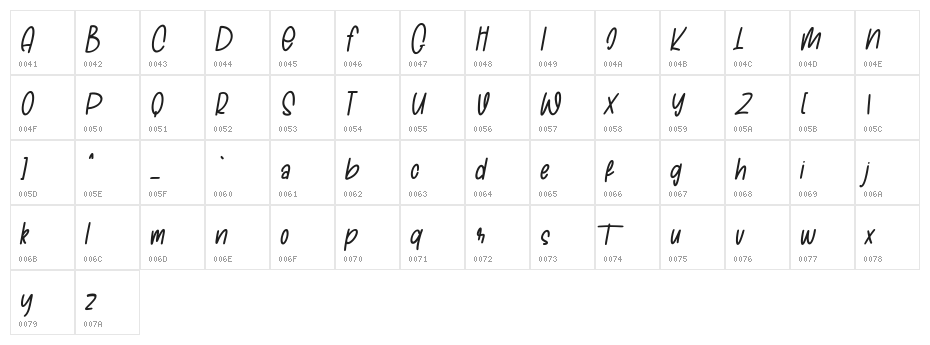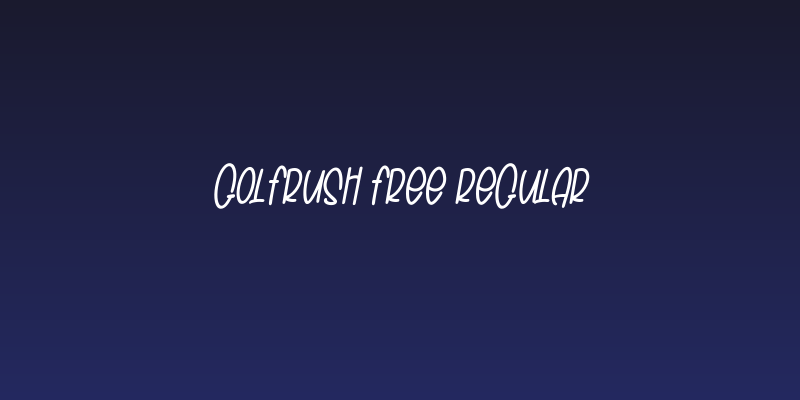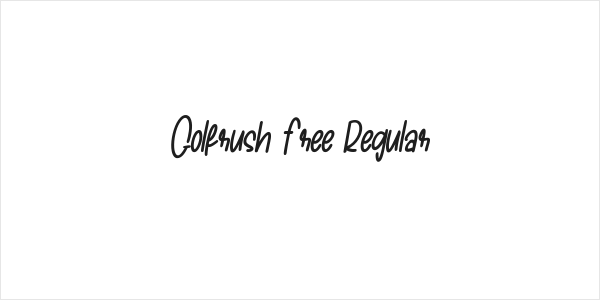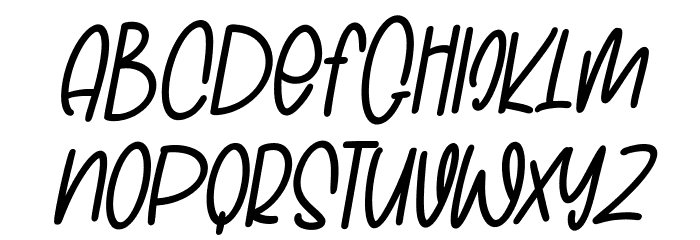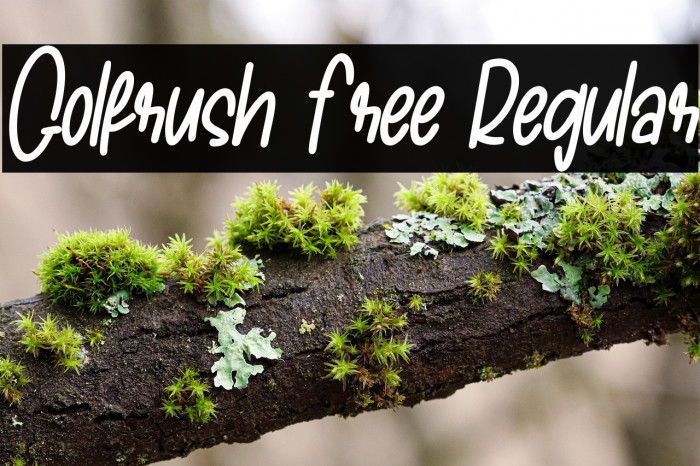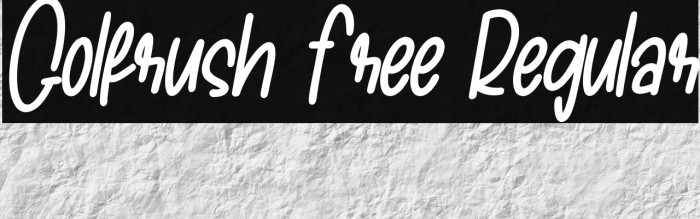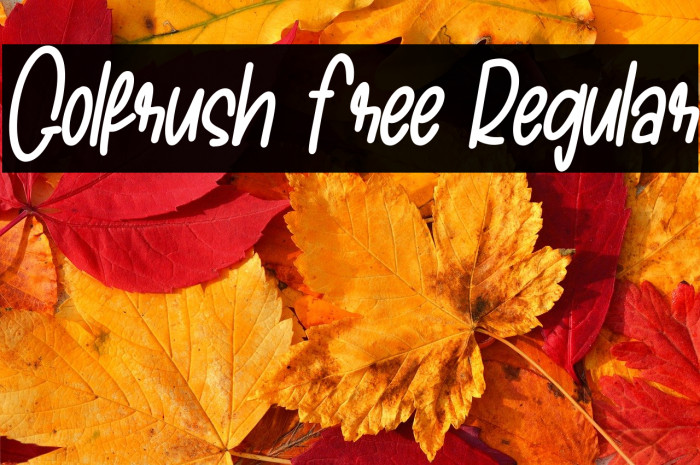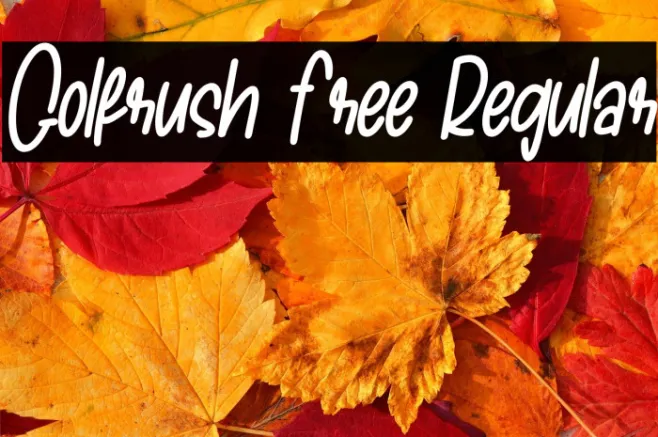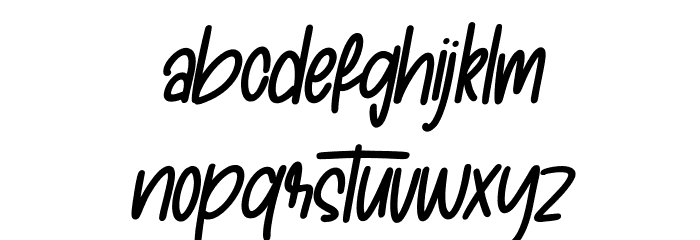
Golfrush Free Regular Font
| Estilo general | Casual |
| Caso de uso | Logos, Invitations, Greeting Cards |
| Proyectos propuestos | Ideal for projects that require a personal touch, such as greeting cards, invitations, or branding for creative businesses. |